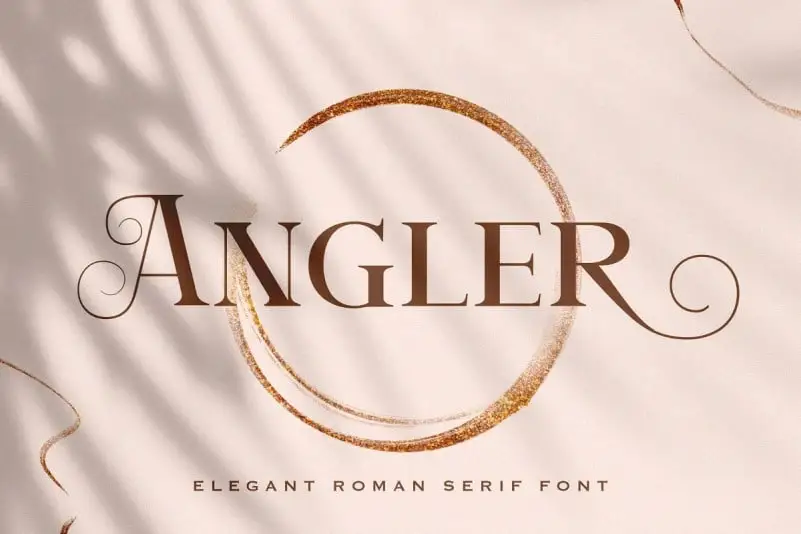
A Angler Serif Font é uma escolha perfeita para quem busca estilo elegante moderno na tipografia serif. Essa fonte inteligentemente usa alternativas para conectar cada letra com um fluxo fluido e suave, criando um resultado único que se destaca em projetos variados. Se você está procurando por uma fonte serifa que combine sofisticação com facilidade de uso, a Angler Serif pode ser sua escolha perfeita. Ela combina modernamente bem com um vasto número de projetos, desde editoriais e publicações até cartões de visita ou marcos de trabalho. Adicione-a aos seus brainstormings e observe como ela eleva os designs mais simples para uma apresentação inovadora. Em nossa coleção de fontes serifa, a Angler é sem dúvida um must-have.